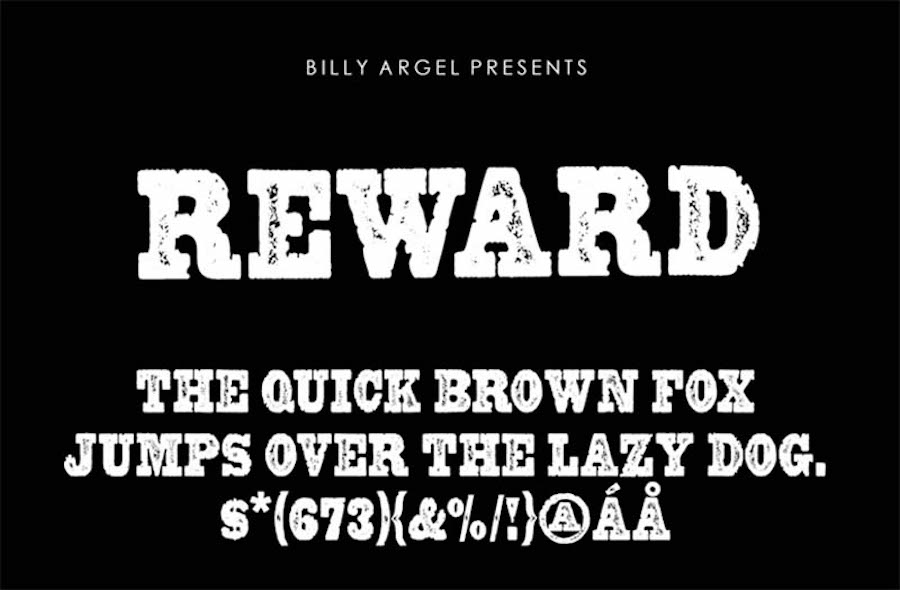
Top 40 Rugged Western Fonts (umfasst kostenlose und Premium-Optionen)
Veröffentlicht: 2021-10-22Wenn Sie an einem Designprojekt arbeiten, das mutig sein und Aufmerksamkeit erfordern muss, ist eine hochwertige, robuste westliche Schriftart möglicherweise die perfekte Wahl. Schriftarten, die an den Wilden Westen, Cowboys, die unerforschte Wildnis und einen freien Geist erinnern, sind eine großartige Möglichkeit, Ihrer Designkomposition Charakter und einzigartigen Stil zu verleihen.
Westliche Schriftarten sind auch ein Dauerbrenner in vielen Designs, die sich auf Typografie konzentrieren, insbesondere für diejenigen, die sich von moderneren Schriftarten entfernen möchten. Westliche Schriftarten sehen auf Postern, Logos, Visitenkarten, Flyern und mehr großartig aus.
In diesem Beitrag haben wir die besten robusten, hochwertigen westlichen Schriftarten zusammengestellt, die Sie in Ihren Designs und auf Ihrer Website verwenden können.
19 kostenlose westliche Schriftarten
1. Boncegro
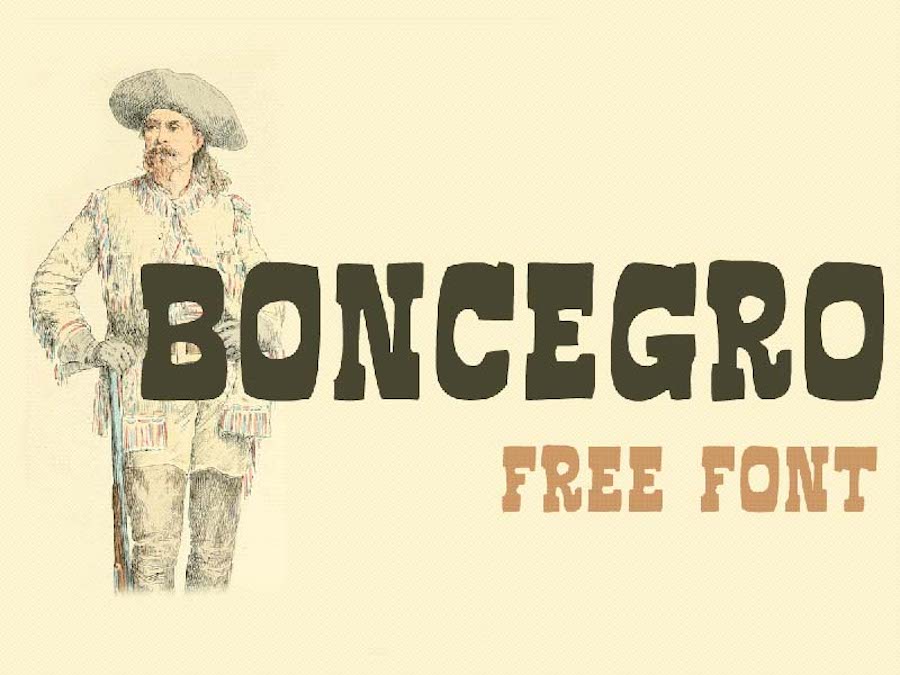
Zunächst einmal haben wir die Boncegro-Schriftart, die sowohl das lateinische als auch das kyrillische Alphabet unterstützt. Es hat viel Charakter und wäre perfekt für Poster und Logos. Die Schriftart ist für den persönlichen und kommerziellen Gebrauch kostenlos.
2. Klipan Schwarz
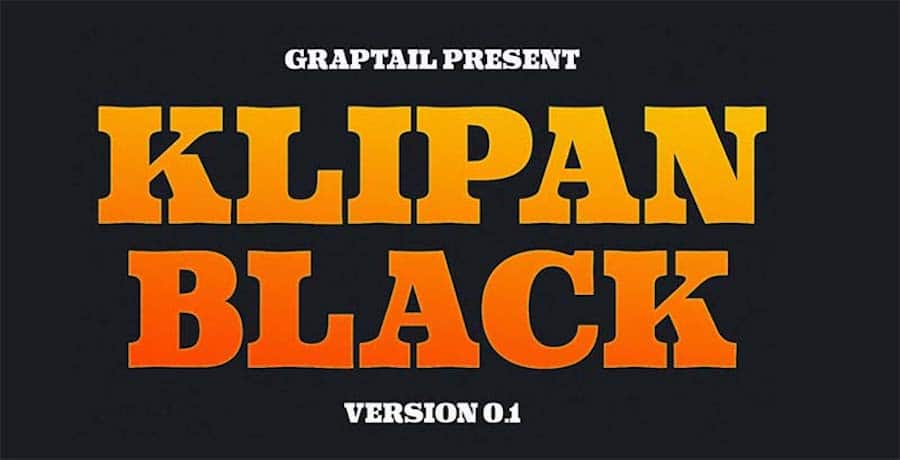
Holen Sie sich mit Hilfe dieser erstaunlichen Schriftart den Look von Old-West-Fahndungsplakaten. Klipan Black enthält mehr als 219 Glyphen. Die Schriftart ist mehrsprachig und eignet sich gut für Logodesign, Poster, Speisekarten und mehr. Es ist unter der Open Font License lizenziert und kann sowohl in persönlichen als auch in kommerziellen Projekten verwendet werden.
3. UNDRRTD
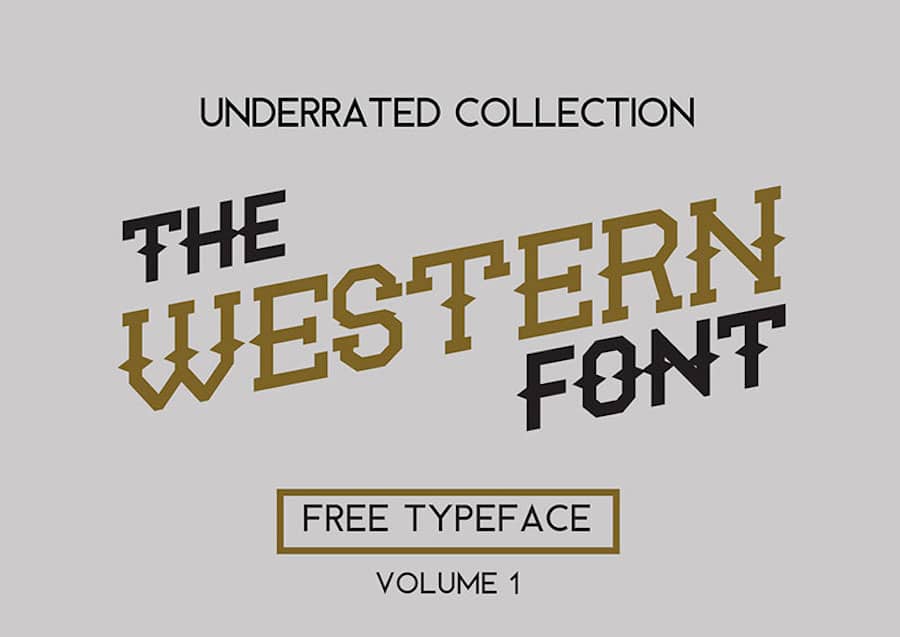
UNDRRTD ist wirklich eine unterschätzte Schrift; es ist voller Persönlichkeit. Es ist eine erstklassige Wahl, wenn Sie möchten, dass Ihr Design Eindruck macht. Die Schriftart wird mit einer Reihe grundlegender Groß- und Kleinbuchstaben geliefert und kann in kommerziellen und persönlichen Projekten verwendet werden.
4. Die Sherloks
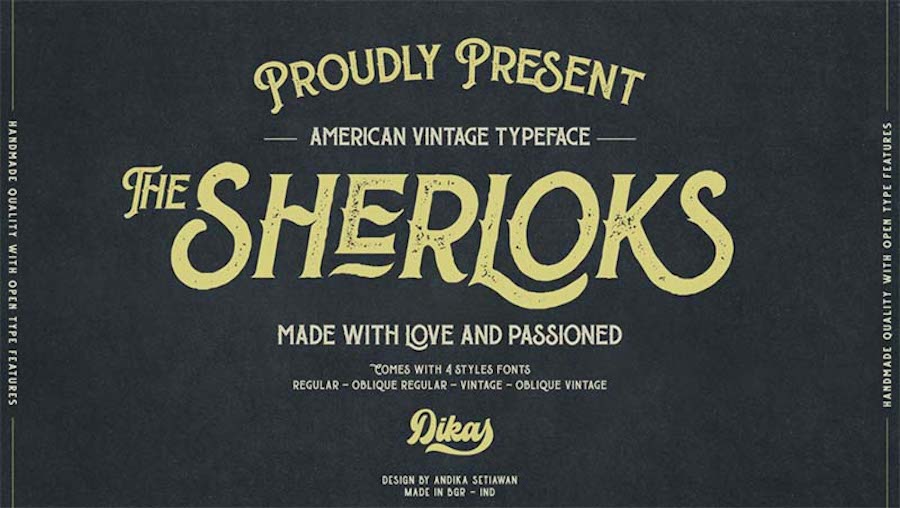
Die Sherloks ist eine vom Americana-Stil inspirierte Vintage-Schrift. Es ist in vier verschiedenen Stilen erhältlich: Regular, Oblique Regular, Vintage und Oblique Vintage. Es enthält mehr als 88 Zeichen und eine Reihe von Ligaturen, um wunderschöne typografische Designs zu erstellen. Sie können es in jedem Vintage-Design verwenden, einschließlich Branding, Logos, Produktverpackungen, Einladungen, Zitaten, T-Shirts, Etiketten, Postern und mehr. Die Schriftart ist für persönliche Projekte kostenlos.
5. Bonaparte
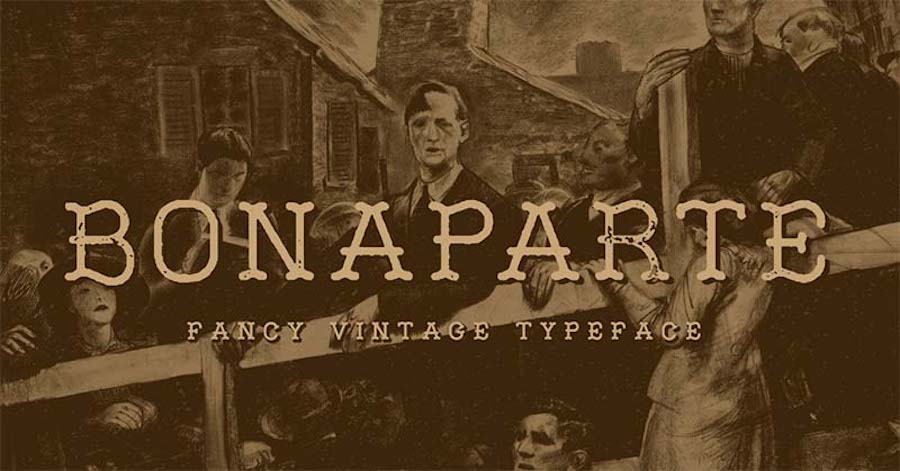
Diese Schrift ist von der Kultur des Alten Westens beeinflusst und hat ein robustes, aber elegantes Erscheinungsbild. Es hat mehrsprachige Unterstützung und kommt mit acht Schriftstilen, alternativer Alphabetform, Ziffern und Glyphen in Groß- und Kleinbuchstaben. Sie können die Bonaparte-Schriftart mit normalem Gewicht kostenlos herunterladen und sie in persönlichen und kommerziellen Projekten für Branding, Verpackungen, Einladungen und mehr verwenden.
6. Kaktus
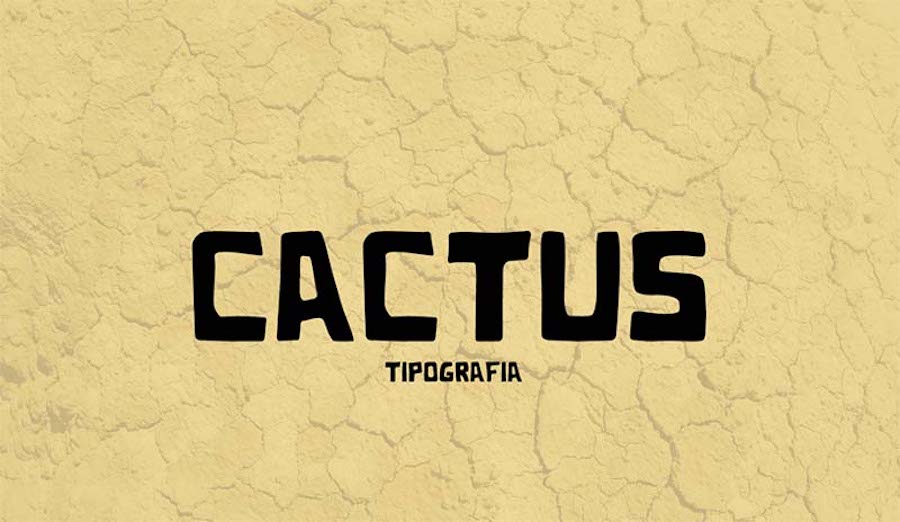
Diese Schrift erinnert an die Kakteen und Wüstengebiete des Westens, ist mutig und hebt Ihre Designs hervor. Es enthält eine Reihe grundlegender Alphabet-Glyphen, Ziffern und Satzzeichen. Die Schriftart Cactus Western kann sowohl in persönlichen als auch in kommerziellen Projekten kostenlos verwendet werden. Es funktioniert gut im Logo- und Posterdesign oder überall dort, wo Sie große Überschriften benötigen.
7. Wayne
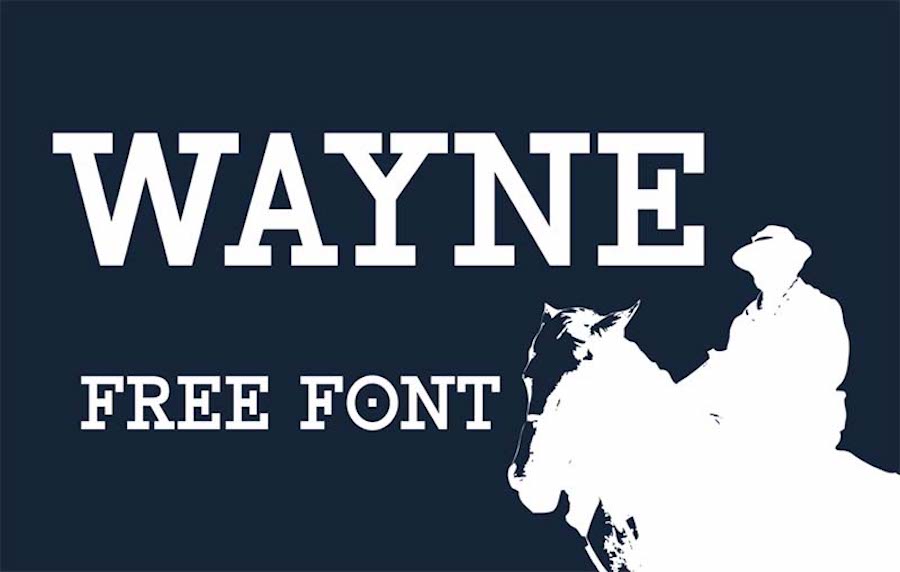
Die Wayne-Schriftart ist von den Spaghetti-Western und Schauspielern wie Clint Eastwood und John Wayne inspiriert. Es wurde von Brave Lion Fonts erstellt und ist eine kostenlose Version der klassischen westlichen Slab Serif. Die Schriftart ist eine großartige Wahl für Poster und Anzeigezwecke, und Sie können sie sowohl in kommerziellen als auch in persönlichen Projekten verwenden.
8. Roadstore
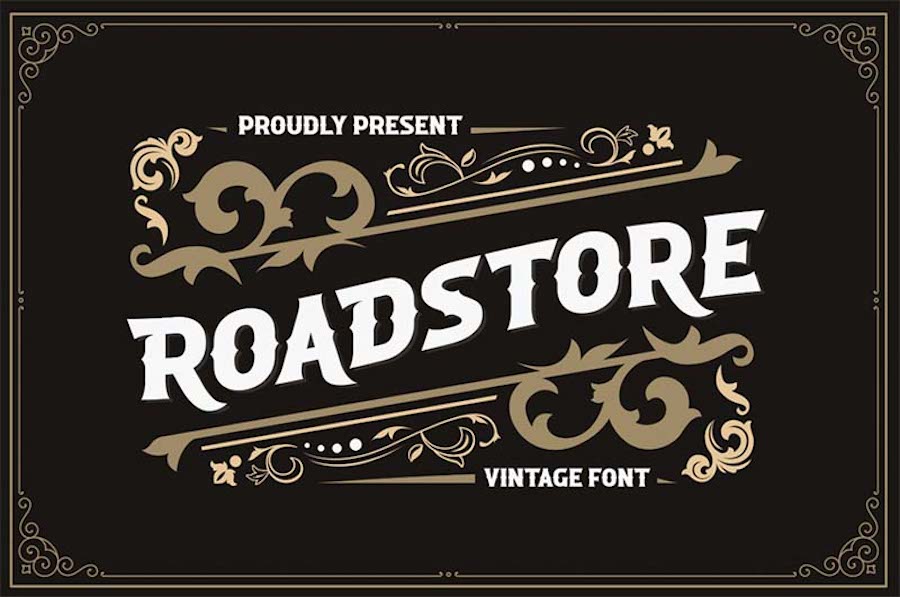
Wenn Sie nach einer Western-Schriftart mit Flair suchen, ziehen Sie die Verwendung der Roadstore-Schriftart in Betracht. Es ist kostenlos für den persönlichen Gebrauch und eignet sich gut für jedes Design, das eine fette Cowboy-Schriftart benötigt, um hervorzustechen.
9. Sherlock-Presse
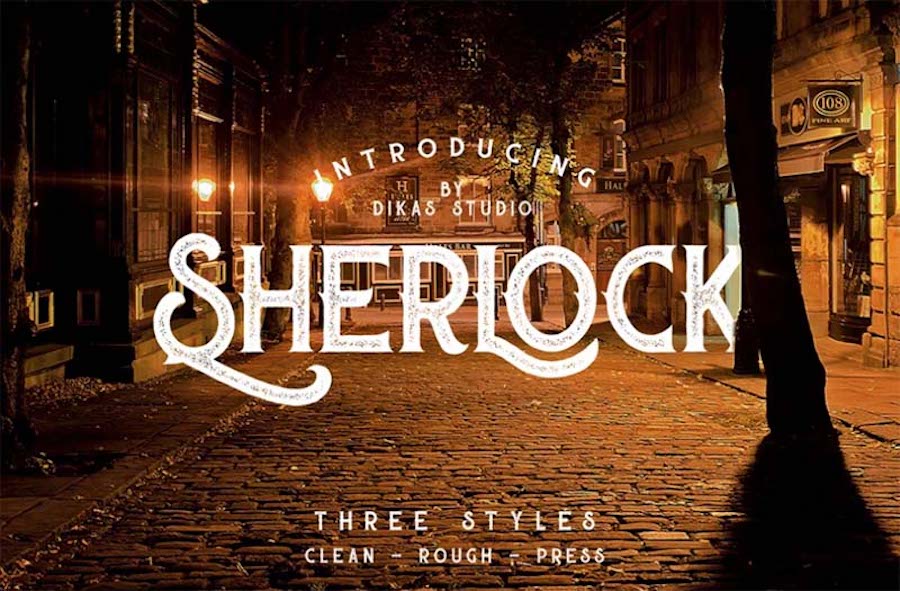
Die Studioschrift Sherlock Press hat ein elegantes Vintage-Feeling. Es ist in drei verschiedenen Stilen erhältlich: rau, gepresst und sauber, wodurch es für verschiedene Projekte geeignet ist. Diese westliche Schrift in Großbuchstaben eignet sich perfekt für Logos, Poster, Etiketten, Verpackungen und mehr. Es ist kostenlos für den persönlichen Gebrauch.
Wie Sie sehen können, gibt es keinen Mangel an hochwertigen westlichen Schriftarten, sowohl kostenlos als auch kostenpflichtig. Jetzt müssen Sie nur noch Ihre Favoriten herunterladen und in Ihrem Projekt verwenden.